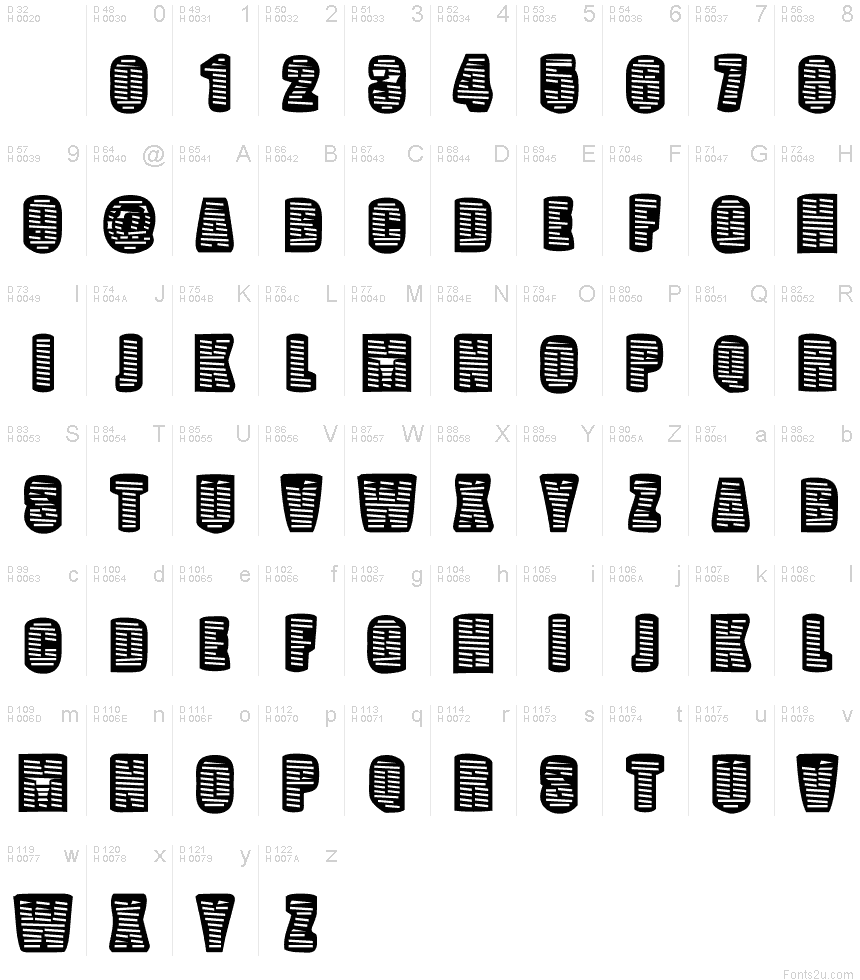
Pop Will Eat Itself, erstellt mit Fontographer 4.1, ist eine kostenlose, gestreifte Pop-Art-Display-Schrift mit einem wuchtigen, plakativ anmutenden Charakter. Die Versalien bestehen aus schweren schwarzen Silhouetten, die von unregelmäßigen horizontalen Bändern durchzogen sind, wodurch die Buchstaben gleichzeitig solide und flackernd wirken – wie handgemalte Schilder, die man durch eine TV-Störung betrachtet.
Die Schrift eignet sich perfekt für Club-Flyer, Zines, Plattencover, plakative Schlagzeilen und Titel, bei denen ein kostenloser Font allein die gesamte grafische Stimmung tragen kann. Da die Buchstaben primär als massive Blöcke und erst in zweiter Linie als gemusterte Formen wahrgenommen werden, funktioniert die Schrift auch hervorragend für kurze Cover-Texte und Monogramm-Logos, die einen rauen, urbanen Edge benötigen.